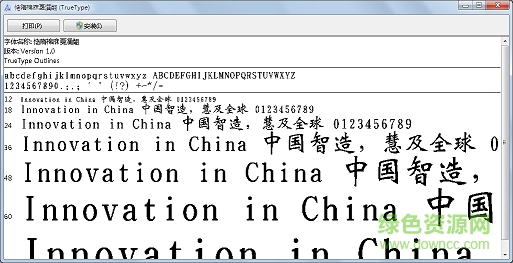
gbweibei bold字體又叫文鼎粗魏碑簡(jiǎn)體,這款字體構(gòu)造嚴(yán)謹(jǐn),筆畫流暢,字形端正又不失靈動(dòng),字形樸厚舒暢,歡迎大家在綠色資源網(wǎng)免費(fèi)下載!
文鼎粗魏碑字體與楷體字效果有點(diǎn)類似,不管是文書纂寫還是用于設(shè)計(jì)都非常合適,喜歡的話就不要錯(cuò)過啦。如果文鼎粗魏碑是你需要的字體,就趕緊來吧!
魏碑是楷書的一種,魏楷和晉朝楷書、唐朝楷書并稱三大楷書字體。魏碑表現(xiàn)出由隸書向典型的楷書發(fā)展過程中的一些過渡因素。